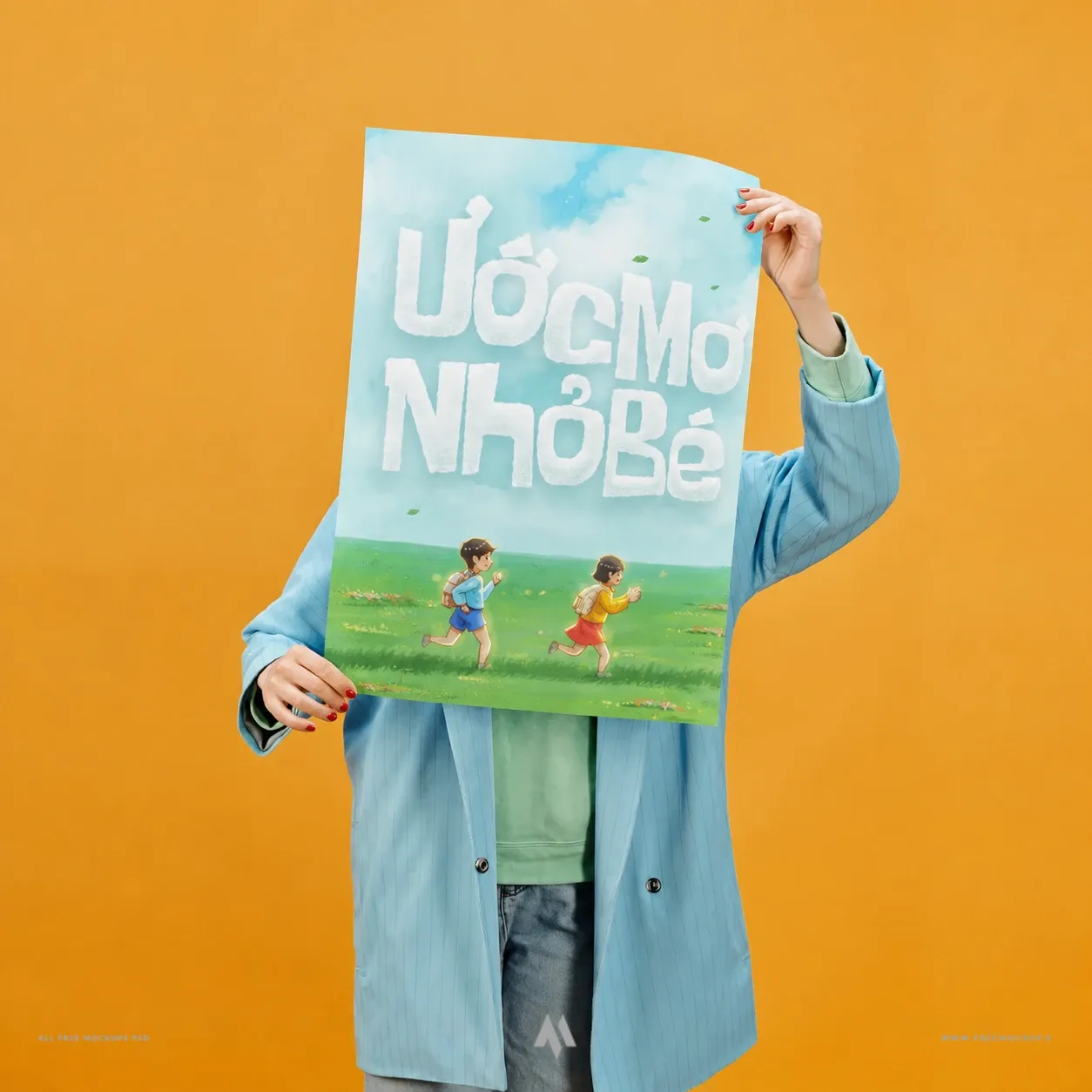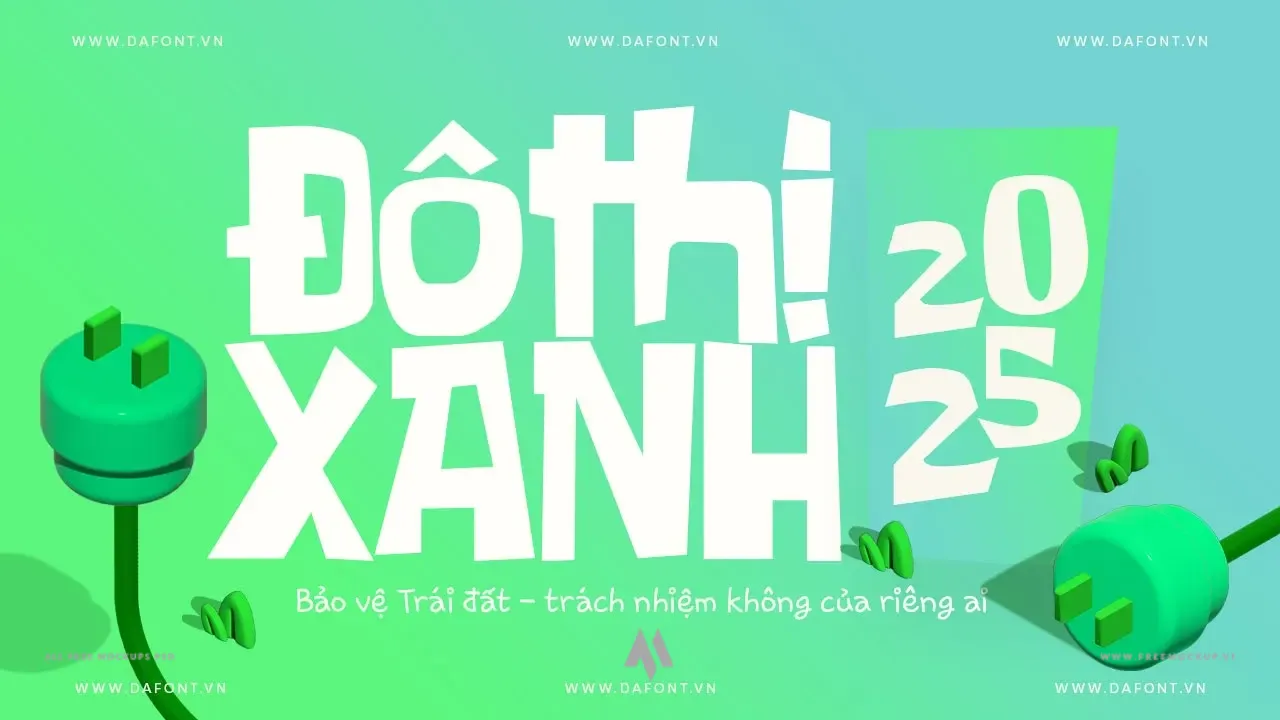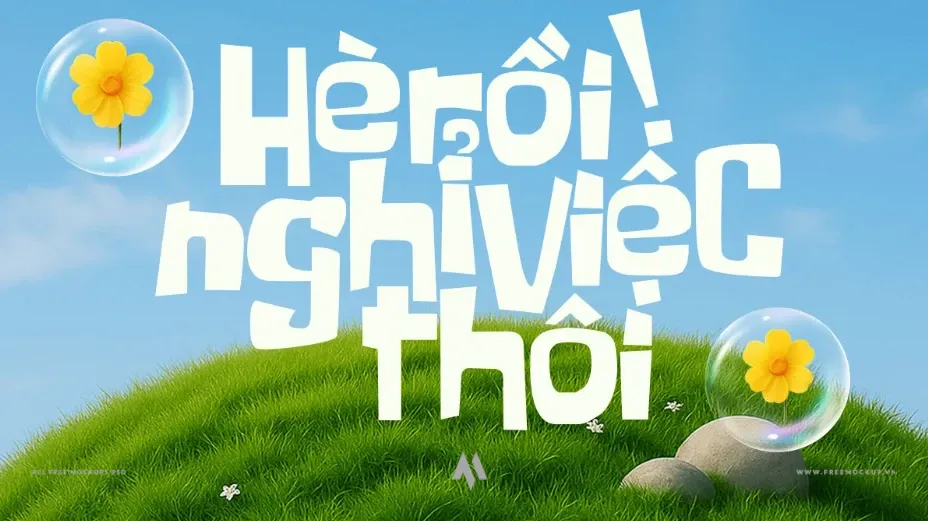
Nếu là một “tín đồ” của loạt phim hoạt hình nổi tiếng SpongeBob SquarePants, chắc chắn bạn sẽ không thể quên những phân cảnh chuyển cảnh thời gian kinh điển như “Two Hours Later”, “A Few Inches Later” hay “One Eternity Later”.
Some Time Later chính là sự tái hiện hoàn hảo phong cách typography mang tính biểu tượng này – vừa hài hước, ngộ nghĩnh lại mang đậm chất hoạt hình meme quen thuộc.
Được thiết kế bởi tác giả Fredrick Brennan, font chữ mang nhiều điểm nhấn ấn tượng:
- Nét chữ bất đối xứng & thủ công: Các đường nét gãy khúc, góc cạnh tự do tạo cảm giác vẽ tay mộc mạc, gợi nhớ về thời kỳ truyền hình và hoạt hình retro kinh điển.
- Phong cách vui tươi, giàu tính biểu cảm: Cực kỳ bắt mắt khi sử dụng làm tiêu đề, thumbnail YouTube, video meme ngắn trên TikTok, poster trẻ em hoặc áo thun.
- Độ nhận diện cao: Dễ dàng tạo ấn tượng mạnh mẽ và gợi nhắc cảm xúc hoài niệm cho người xem ngay từ cái nhìn đầu tiên.